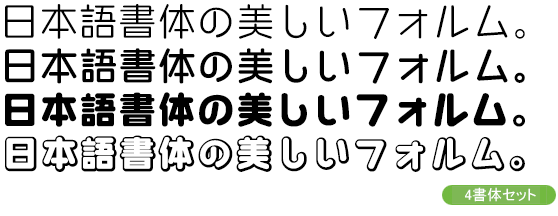
シーモ3書体+オープンタイプ
柔らかさより、幾何学的なフォルムをイメージしてデザインしました。タイトルなどで、やや大きく使用すると面白い書体です。シーモ3書体(中細丸/中丸/太丸)+ シーモオープンボールドの4書体セット。
CFONTは下島正人氏が手掛けるフォントライブラリー。キャッチコピーやタイトルを目的としたディスプレイタイプフォントを制作しており、個性的なフォルムを重視しながらも可読性も考慮されたデザインが特徴です。